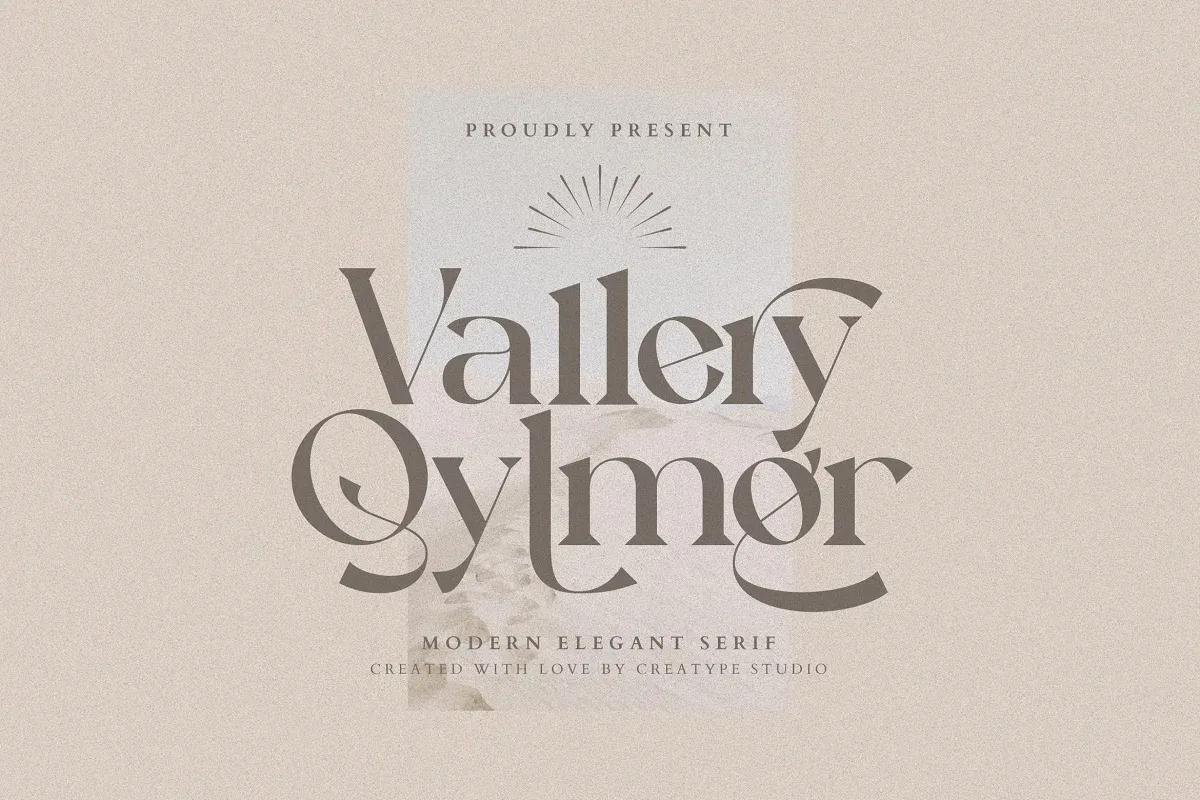
Vallery Qylmor Font – Download Grátis
Vallery Qylmor é uma elegante e moderna fonte serif perfeitamente adaptada para qualquer projeto de design. Seus traços cuidadosamente delineados trazem sofisticação a qualquer layout, tornando-a uma opção perfeita para grandes projetos. Esta fonte é uma criação de um designer habilidoso que busca manter a essência do estilo serif enquanto adota um toque moderno e contemporâneo. Perfeito tanto para o design editorial quanto para logotipos ou letras de texto, Vallery Qylmor se destaca por sua simplicidade e elegância, garantindo sempre uma experiência visual envolvente em qualquer projeto que ela faça parte. Seja você um profissional de design ou alguém que simplesmente busca novas opções para seu trabalho, este é definitivamente o tipo de fonte que pode transformar seus projetos em verdadeiras obras de arte.